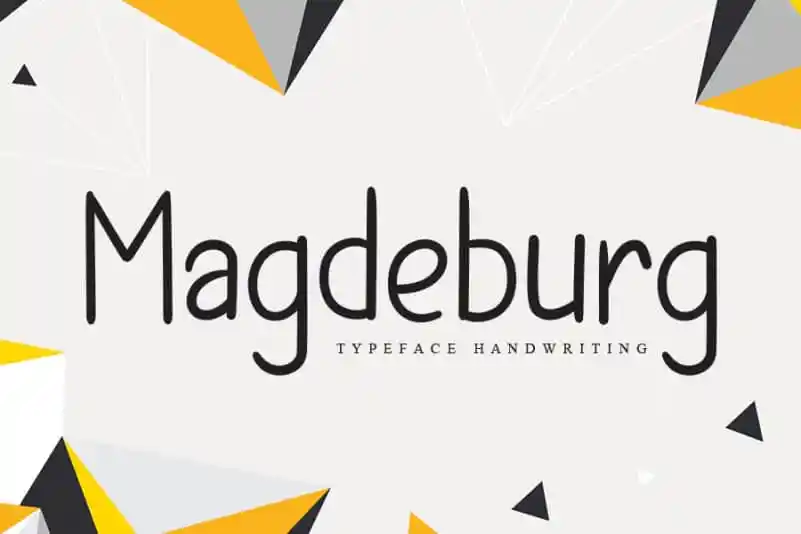
Magdeburg Handwritten Font – Fonte Grátis
Magdeburg Handwritten Font
A Magdeburg Handwritten Font é uma fonte escrita à mão que traz beleza moderna e versatilidade perfeitas para diversos usos. Embora seja desenhada para textos a mão, sua elegância e simplicidade permitem seu uso em várias aplicações, desde design de web até impressão. Perfeito para headlines grandes ou pequenas, este tipo também é ótimo para blocos de texto que vão do máximo ao mínimo em variação. Tanto se usa na tela quanto offline, Magdeburg manterá sempre a sua elegância e profissionalismo. Seja você designer web, editor de fotos ou ilustrador de livros, Magdeburg será uma escolha inteligente para dar um toque único aos seus projetos.